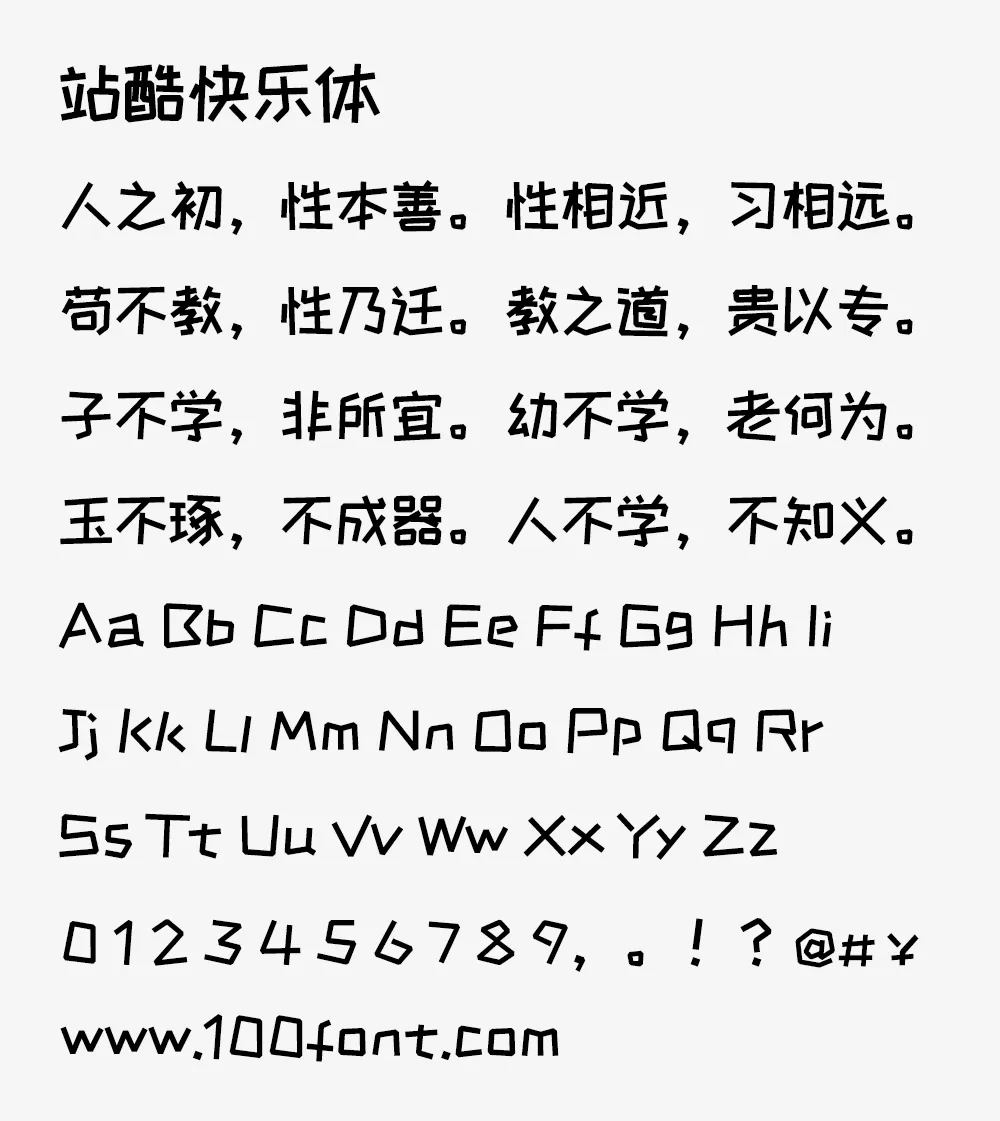
站酷快乐体
「站酷快乐体」是一款由字体设计师刘兵克牵头打造的字体作品。这款字体的诞生源于一场字体设计共创活动:刘兵克率先敲定字形框架与设计规范,再由一百多位学员分工完成基础字形的绘制,最后交由刘兵克字体设计工作室的杨康、吴少杰两位设计师进行统一的修改与调校,于 2015 年 9 月正式发布。
而「站酷快乐体 2016 修订版」,则是在初代版本的基础上完成的全面升级与优化。该版本的前期设计工作由刘兵克的学员团队与工作室团队联手推进,后期则由刘兵克本人逐字打磨调整,历经多轮严格校审,耗时整整 7 个月,最终在 2016 年 6 月正式上线并开放下载。
站酷快乐体于2018年11月20日上传至谷歌字体,并以SIL Open Font License 1.1授权释出。2021年5月13日,站酷设计师@skr_ZERO子发布站酷快乐体部分汉字字形问题依旧存在,于是便进行了修正并发布了新的版本。